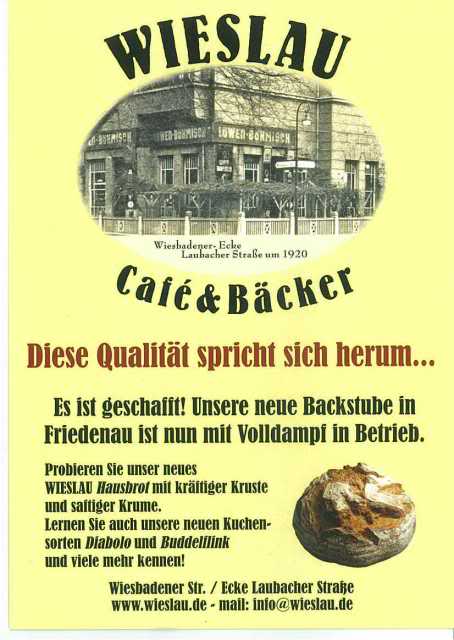
ich werde fast irre, weil ich die passende Schrift für meinen Kunden nicht finde. Wer kann weiterhelfen. Welche Schrifttype ist im Schriftzug "Wieslau" und welche im Copxtext verwendet worden?
Mal stimmt das "W", dann ist garantiert das "S" falsch.
Und für die Bildunterschrift:
Von der Bernhard Antique gibt es keine Kursive, die Gangster, die den Zettel gemacht haben, haben also einfach die Schrift schräggestellt. Unter Typographen kann das dazu führen, daß man geteert und gefedert wird. Außerdem sieht es nicht so gut aus.
Hey, vielen Dank, das ist echt klasse. Das mit dem Teeren kann ich nur unterschreiben, aber verständlicherweise will der KD keine Modifikation und ich weigere mich mit einem getracten Element zu arbeiten. Aber die Jungs die das mal verzapft haben sind eben chon gaaaanz lange nicht mehr!!!
Darfst Du dann wenigstens ein Leerzeichen vor die Auslassungspunkte setzen? Und die "neuen" Produkte sind ja inzwischen wohl auch nicht mehr sooo neu – trotzdem keine Modifikationen?
Ja das geht schon! KD ist nur sehr scharf auf die Wortmarke. Andere Modifikationen dürfen inzwischen entsprechnd seiner "frischen Produkte" umgesetzt werden!